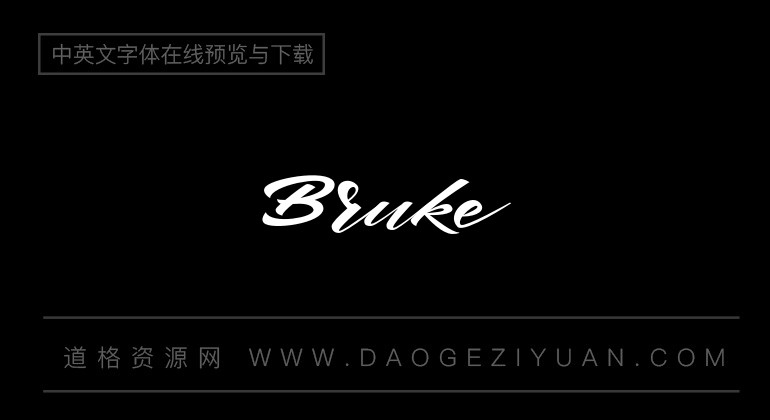
Bruke 字体是一款英文字体,由英国设计师 Steve Matteson 创作,属于现代系列字体。它以细节精致的外观和特色的字形设计而闻名,是一款非常适合用于海报、品牌标识、书籍封面、媒体活动等场景的字体。Bruke 字体具有优雅、大气、精致的特点,能够有效地提升文字表达的视觉效果,使用它可以给你的文字创作带来更好的体验。内容介绍
Bruke是一款非常不错的手写艺术字体,具有很好的视觉感,适合于文化类的宣传设计、商业类品牌的广告和产品包装设计以及个性化文字排版等较多场景。